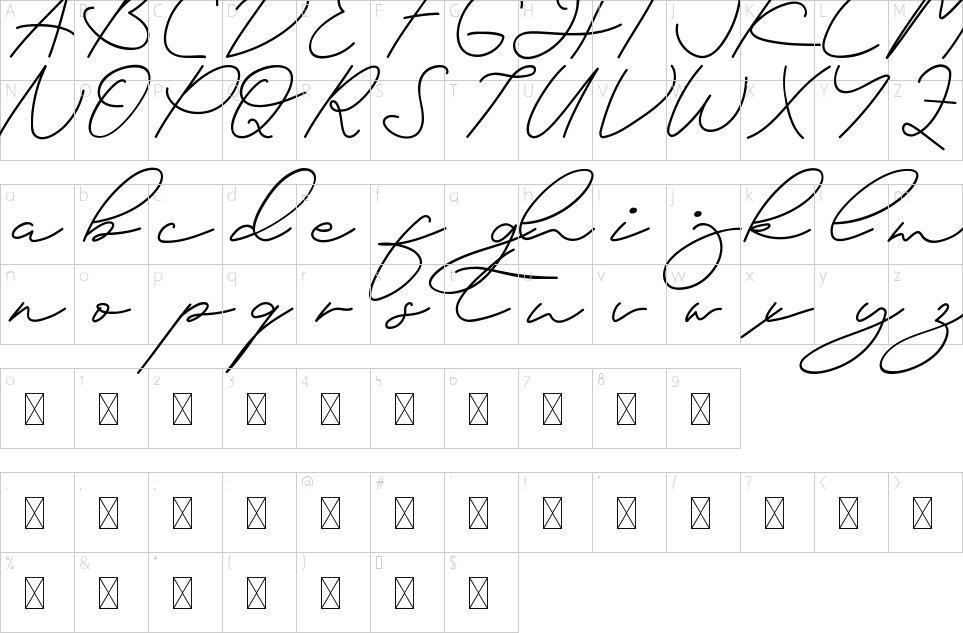
Dreamy Melodies Font – Download Grátis
Descubra a magia do som nos traços delicados da Dreamy Melodies Font. Desenvolvida por EdricStudio, esta fonte gratuita oferece uma experiência visual única para quem busca um toque romântico e evanescente em seus projetos digitais. Com traços suaves e harmoniosamente elegantes, a Dreamy Melodies proporciona um ambiente de tranquilidade e reflexão ideal para ambientes que valorizam emoções sutis. Seja em uma página de leitura ou como parte do design de um projeto editorial, o charme da Dreamy Melodies irá tornar seu trabalho ainda mais especial. Esta fonte está disponível tanto para sistemas Windows quanto Mac, permitindo-lhe experimentar a magia sem limitações. Com apenas 2.214 downloads até agora, é uma opção popular entre designers que procuram um toque único e delicado em seus projetos.